Sebentar lagi bukan ramadhan akan segera dimulai, berbagai persiapan sudah mulai terlihat termasuk dalam berbagai desain branding. Penting untuk berbagai brand mengikuti perubahan desain yang disesuaikan tema ramadhan untuk event yang segera berlangsung ini. Penggunaan elemen visual warna desain tema ramadhan termasuk font, gambar, dan warna akan mendukung branding yang profesional.
Setiap tahunnya ketika ramadhan dimulai berbagai akan mulai mengganti tema desain dalam berbagai kebutuhan agar relevan. Untuk menyambut ramadhan berbagai desain grafis akan mencerminkan visual islami dan damai. Bahkan beberapa ada yang memproduksi produk atau layanan khusus ramadhan, ini akan berguna memperkuat branding.
TEMA DESAIN RAMADHAN
Desain grafis tema ramadhan dibuat agar brand relevan dengan tren dan event saat ini, hal ini akan memastikan brand berkesan profesional. Tema ramadhan akan menghiasi berbagai jenis desain, mulai dari website, media sosial, banner hingga kemasan khusus ramadhan. Adapun berikut elemen-elemen visual khas desain tema ramadhan:
Menggunakan Elemen Visual Khas Ramadhan
Untuk menciptakan desain grafis yang menarik sesuai tema Ramadhan, gunakan berbagai elemen visual khas ramadhan. Beberapa diantaranya menggunakan gambar kubah atau menara masjid, bulan sabit, lampu gantung hingga pola geometris islami. Dekorasi berupa gambar kaligrafi arab dengan makna tertentu akan mendukung visualnya.
Warna Sederhana, Mewah dan Islami
Penggunaan warna yang sesuai dengan tema ramadhan salah satunya warna khas islami seperti hijau dan biru kehijauan. Warna hijau bisa dikombinasikan dengan warna emas agar tampil mewah dan berkesan damai. Selain itu bisa juga mengkombinasikan warna:
- Biru dan Silver Tua: Kombinasi ini bisa menciptakan kesan yang elegan dan menyenangkan.
- Ungu dan Coklat: menciptakan kesan hangat dan spiritual, penting untuk mengatur saturasinya agar harmonis.
- Putih: Ini digunakan sebagai warna dasar agar kombinasi warna lebih harmonis dan menciptakan desain yang sederhana.
Tipografi Elegan dan Bersih
Gaya Tipografi untuk desain tema ramadhan akan relevan menggunakan font yang elegan, bersih dan ramah. Selain itu juga biasanya memiliki font dengan sentuhan kaligrafi Arab atau seperti gaya huruf arabic. Penggunaan font elegan bertujuan untuk menciptakan mewah, sementara handwritten akan tampil lebih hangat dan menyenangkan.
Layout Sederhana, Rapi dan Bertekstur
Desain poster tema ramadhan akan menyusun elemen-elemen visual tersebut pada layout yang sederhana, rapi dan bertekstur. Gaya layout yang simpel akan fokus pada penggunaan gambar utama seperti kubah atau bulan sabit saja.
Biasanya desain juga akan menggunakan geometris islami sebagai dekorasi dan digunakan secara simetris pada sudut halaman. Terkadang desain juga akan memiliki tambahan komposisi berupa efek cahaya lembut, gradasi warna atau motif islami.
CIRI FONT RAMADHAN
Gaya tipografi yang digunakan dalam desain ramadhan akan menyesuaikan dengan tema desain ramadhan. Jika desain ramadhan identik dengan desain yang sederhana, elegan dan mewah maka tipografi harus relevan. Beberapa desain tema ramadhan seringkali menggunakan ciri font seperti:
Elegan dan Ramah
Seringkali desain tema ramadhan menggunakan desain visual yang elegan, mewah dan menyenangkan. Untuk mendukung visual ini maka gunakan font yang memiliki garis halus yang elegan dan bersih. Biasanya font akan memiliki sentuhan islami dan gaya huruf modern geometris sehingga mudah dibaca. Tipografi juga akan memiliki lekukan lembut dan nuansa font yang premium atau mewah.
Font Serif Sentuhan Islami
Desain tema ramadhan juga sering kali menggunakan font serif yang memiliki sentuhan islami. Gaya serif elegan, halus dan memiliki elemen tradisional seperti ujung serif yang panjang akan relevan untuk tema ramadhan. Serif elegan akan cocok digunakan pada desain banner ramadhan, konten media sosial hingga kemasan khusus ramadhan.
Font Script dan Handwritten
Desain ramadhan yang tampil elegan juga akan relevan menggunakan gaya font script atau handwritten yang elegan. Namun font ramadhan tidak terlalu tipis, biasanya gaya font akan dibuat lebih tebal. Gaya tipografi ini akan menciptakan desain yang berkesan personal dan hangat. Biasanya banyak digunakan pada desain ramadhan untuk kartu ucapan, poster, dan media sosial.
Tipografi Gaya Kaligrafi
Untuk merepresentasikan desain tema ramadhan dengan efektif, biasanya juga menggunakan tipografi bergaya huruf arabic. Style gaya hurufnya akan terlihat memiliki bentuk seperti huruf arabic sehingga bisa merepresentasikan kesan islami. Gaya hurufnya akan memiliki lengkungan indah dan aksen khas, font cocok untuk judul atau elemen dekoratif.
REKOMENDASI FONT RAMADHAN
Ketika menciptakan desain tema ramadhan, perhatikan pemilihan gaya tipografi yang relevan agar menciptakan desain yang menarik. Biasanya ada beberapa jenis font dan gaya huruf yang khas dengan tema desain ramadhan. Berikut beberapa rekomendasi font tema ramadhan:
Berkshire Swash
Desain ramadhan akan relevan menggunakan font serif elegan tersebut yang memiliki garis yang halus dan bersih. Font serif ini memiliki sentuhan klasik dan islami, pada penggunaan serif melengkung.
Lengkungan pada huruf tersebut menciptakan nuansa elegan dan klasik yang khas. Font serif elegan dan sederhana ini bisa digunakan untuk kebutuhan tema desain yang elegan, mewah atau pada headline desain konten. Serif yang agak tebal ini akan memiliki keterbacaan yang baik.
Lobster
Desain ramadhan sering menggunakan style font elegan karena bisa menciptakan visual yang mewah dan indah. Selain serif elegan, font script juga bisa menciptakan gaya tipografi yang elegan, seperti font tersebut.
Gaya font lobster tersebut memiliki gaya huruf bersambung, bersih dan memiliki gaya huruf yang tebal. Style hurufnya memiliki lengkungan yang halus, rapi dan bersih sehingga menciptakan kesan ramah. Font tersebut juga mudah dibaca sehingga bisa digunakan sebagai font judul pada desain banner.
Cinzel Decorative
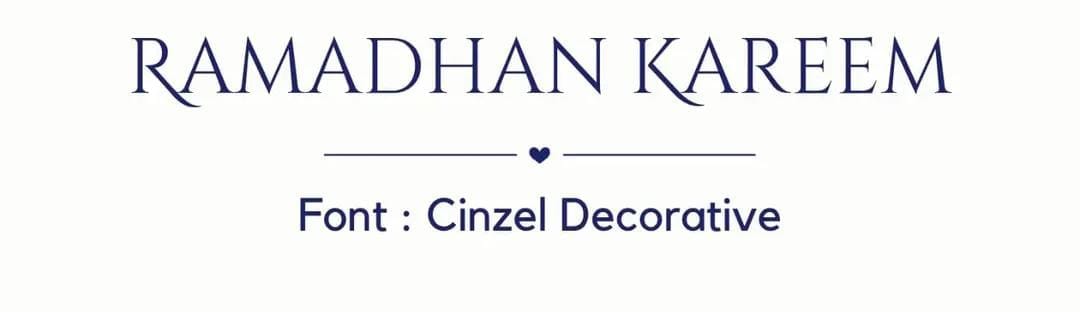
Sementara itu font serif elegan ini memiliki gaya huruf yang lebih tipis dan garis huruf yang elegan. Font tersebut memiliki style serif yang lancip, dan sudut huruf yang tajam sehingga tampil lebih elegan. Gaya tipografi ini bisa digunakan menciptakan desain visual yang elegan.
Untuk menciptakan desain visual yang menarik, gaya font ini bisa digunakan untuk kebutuhan desain kartu ucapan. Desainnya harus memiliki style minimalis sehingga akan tampil mewah dengan font serif tersebut.
Baca juga: Rekomendasi Font Soft Serif untuk Desain Grafis
Kawthar
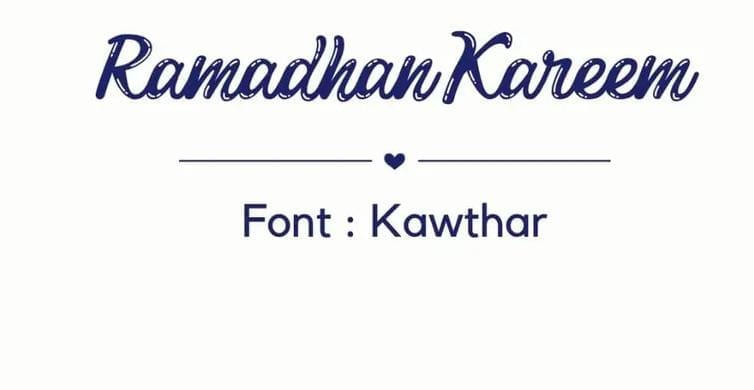
Gaya font tersebut memiliki visual huruf yang tampil ramah dan terlihat seperti tulisan tangan. Font tersebut memiliki style font handwritten yang elegan dan memiliki huruf bersambung. Gaya huruf pada font tersebut juga tampil lebih unik karena memiliki tekstur yang membuat huruf terlihat memiliki efek tiga dimensi.
Penggunaan font handwritten yang unik tersebut akan relevan untuk desain poster atau banner agar menarik perhatian. Untuk digunakan sebagai font judul atau headline, akan menciptakan desain yang lebih menarik dan unik.
Amoresa
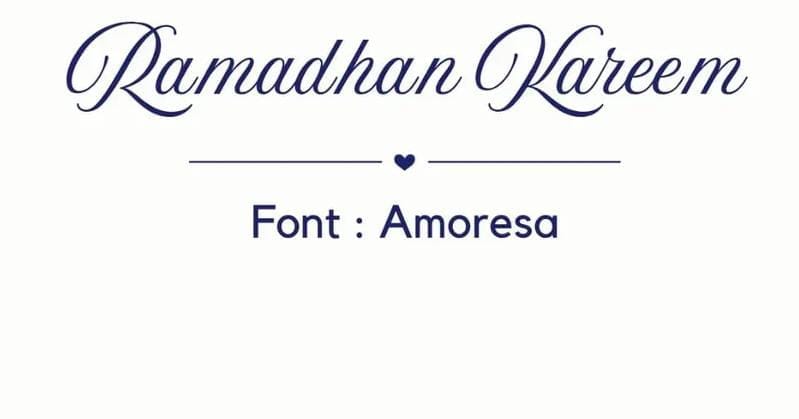
Desain tema ramadhan juga bisa menggunakan gaya font script tipis yang elegan. Penggunaan font script tipis yang elegan bisa menciptakan desain yang mewah dan indah. Font tipis tersebut harus digunakan pada layout desain minimalis agar menciptakan desain yang relevan.
Garis huruf tersebut tampak halus dan memiliki lengkungan indah, serta beberapa memiliki ujung yang panjang dan tajam. Gaya huruf bersambung juga menciptakan visual yang semakin elegan dan mewah. Font ini akan lebih cocok digunakan untuk kartu ucapan ramadhan atau kemasan produk premium.
Dalam menyambut ramadhan berbagai brand dan bisnis akan mulai menciptakan tema desain ramadhan agar relevan. Penggunaan elemen visual khas ramadhan harus efektif dan dipilih sesuai kebutuhan. Termasuk juga dalam memiliki ciri font yang khas dengan desain ramadhan.